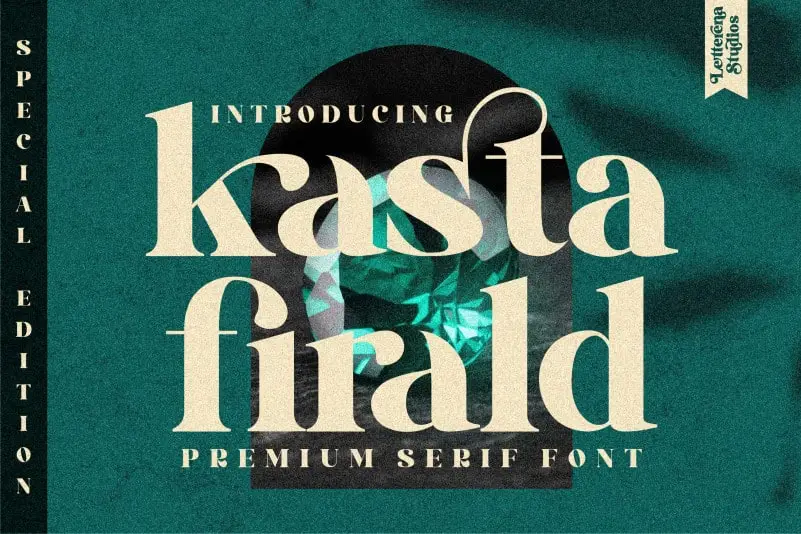
Kasta Firald Serif Font – Fonte Grátis
Kasta Firald Serif Font
A Kasta Firald Serif é uma elegante fonte gótica perfeita para projetos que exigem uma certa sofisticação. Ela foi criada pelo designer letterenastudios e destaca-se por sua robustez e luxo, tornando-a ideal tanto para criações de identidade visual quanto para design gráfico. Com um amplo espectro de aplicações, a fonte se destaca em projetos como logotipos, campanhas de marca, designs de móveis de consumo, embalagens de produtos, chávenas, citações e posters. Ela é ideal também para etiquetas, embalagens de fotografias, marcas, cartões de convite, cartazes de aniversário, selos, água-marinha e eventos especiais em geral. A Kasta Firald Serif atua como uma escolha perfeita para projetos que exigem estilo e sofisticação, proporcionando um toque luxuoso a qualquer projeto, tornando-a perfeita tanto para os mais tradicionais quanto para aqueles com um olhar moderno.